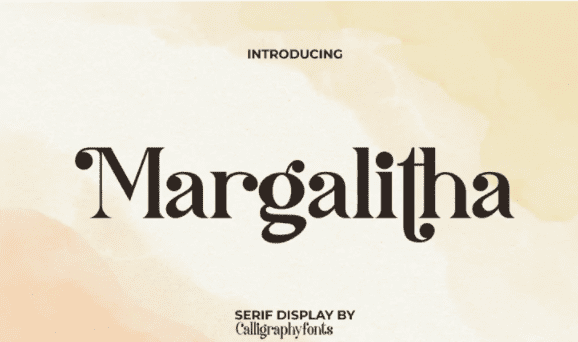
Название: Margalitha Font (2022)
Шрифт Margalitha - это шрифт с засечками, выполненный в стильном стиле. Помимо стильности, этот шрифт обладает современным и уникальным стилем. Отлично подходит для брендирования логотипов, журналов, упаковки продукции, вывесок и т.д. Шрифт Margalitha отлично подойдет для многих отраслей, включая: моду, домашний декор, журналы, упаковку продуктов, вывески и т.д.